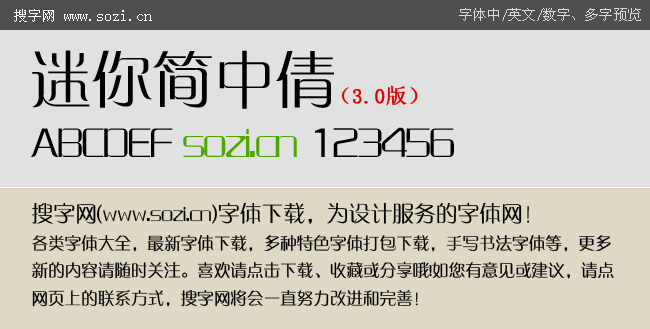
迷你簡(jiǎn)中倩體
搜字網(wǎng)給大家提供一款迷你簡(jiǎn)中倩體下載。中倩體親切、幽雅、柔美和華麗,筆劃粗細(xì)對(duì)比適中,婉轉(zhuǎn)嫵媚,溫順乖巧,看似平淡無(wú)奇,卻能給人以美的感受。適用于個(gè)人用品、化裝品、食品、家居廣告宣傳使用環(huán)境。